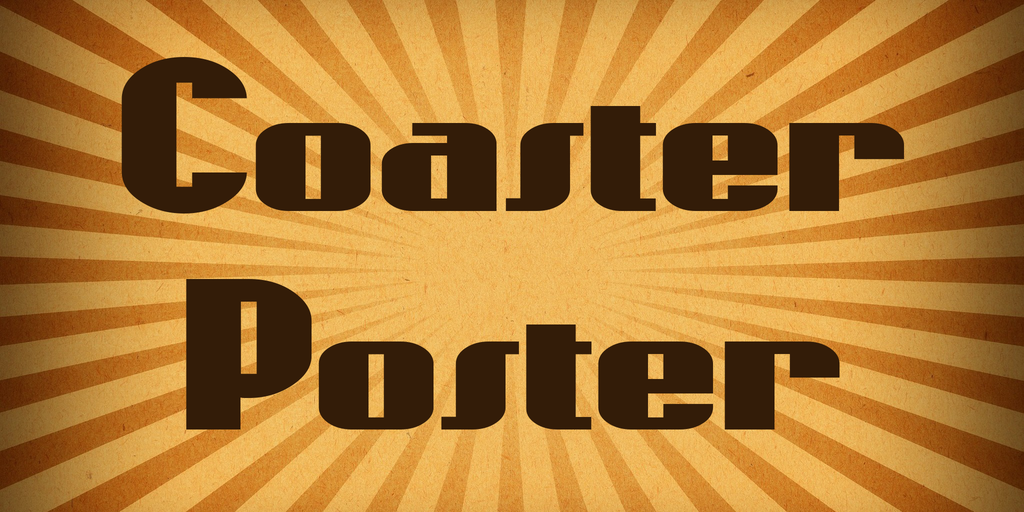
A Coaster Poster Font é inspirada nas famosas bandas de propaganda dos anos 30, feitas a base de silkscreens cortados à mão. Ela é perfeita para aplicação em grandes títulos e chamadas de atenção, proporcionando um ar vintage sem sombra de dúvidas. Com uma tipografia robusta e direta, essa font retrata o espírito dos tempos de posters de rockabilly e cartazes da era das grandes corridas automobilísticas. Perfeito para revistas retro ou marcas de gráficos antigos, a Coaster Poster Font traz um charme vintage à sua próxima arte digital project. Não deixe de experimentar esta font do designer Hamilton, que captura as cores vibrantes e o impacto audível das bandas de rock dos anos 50 e 60.